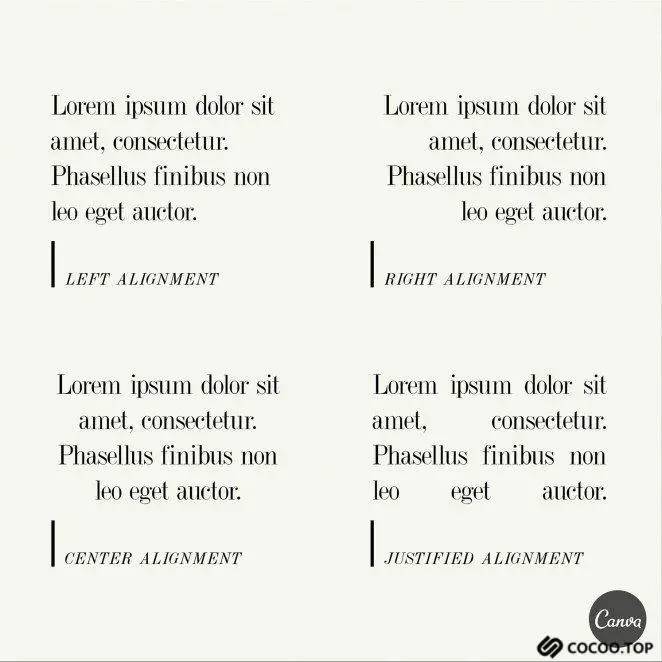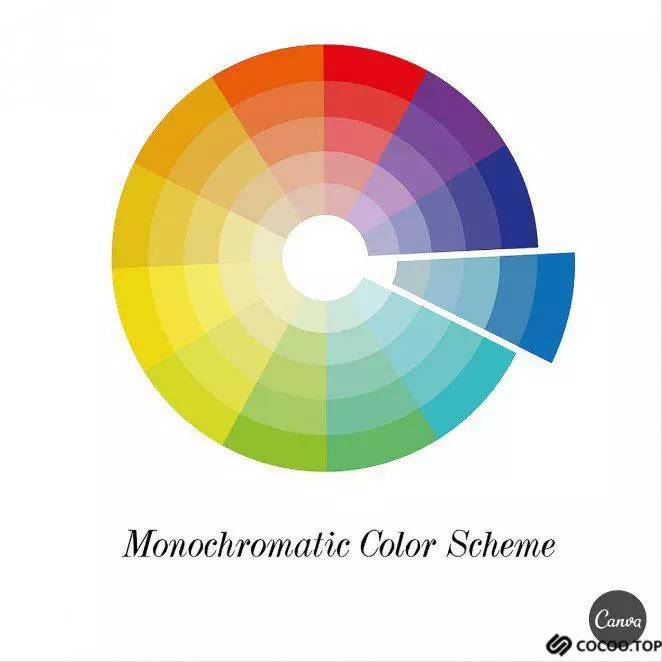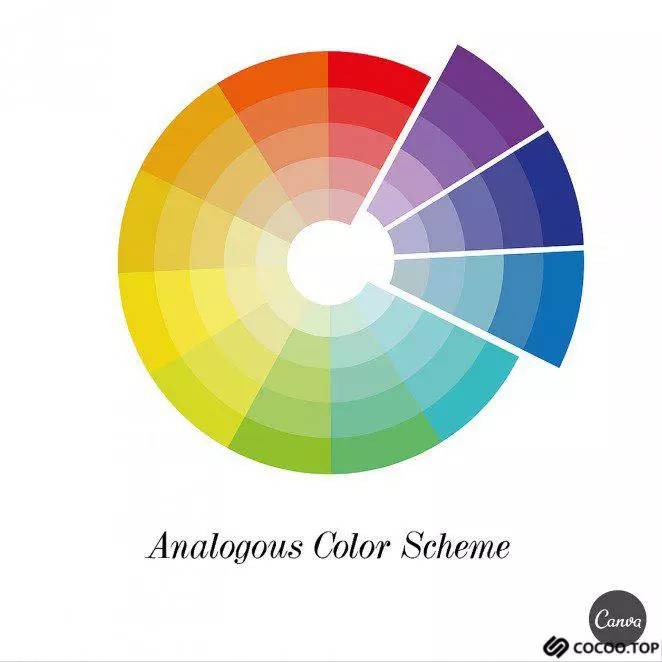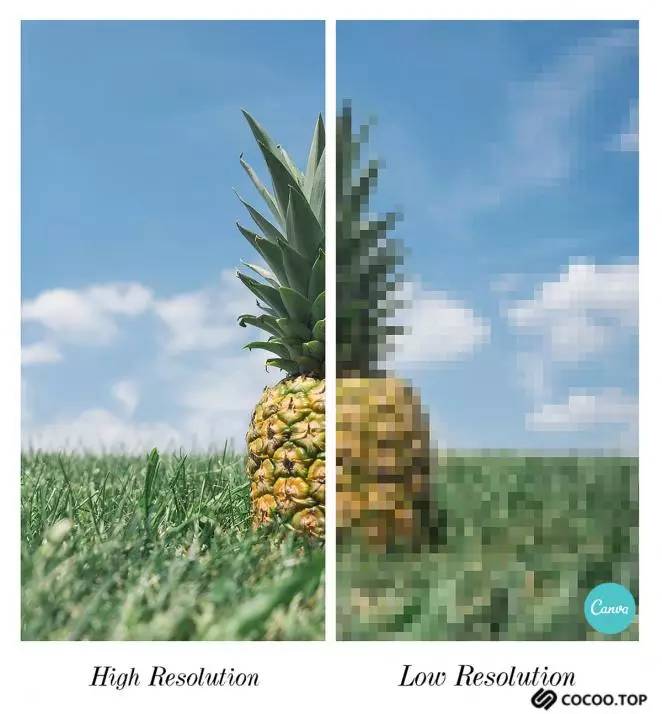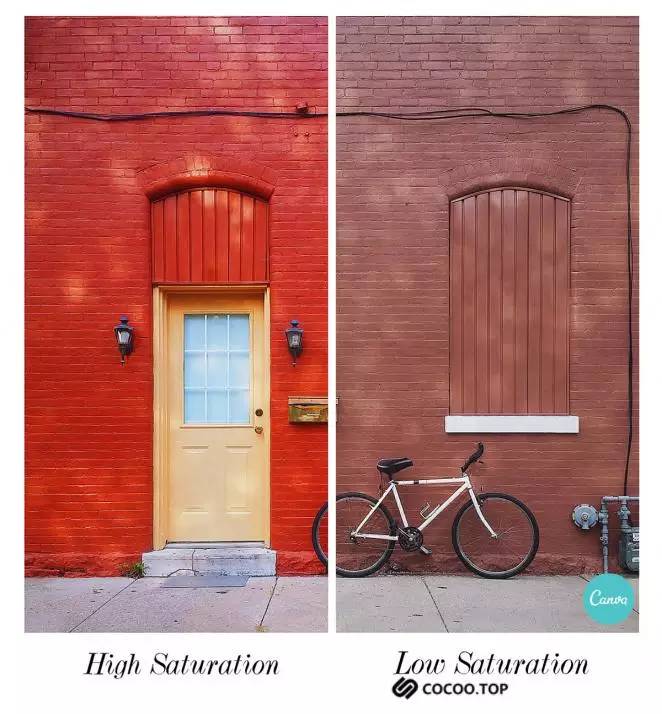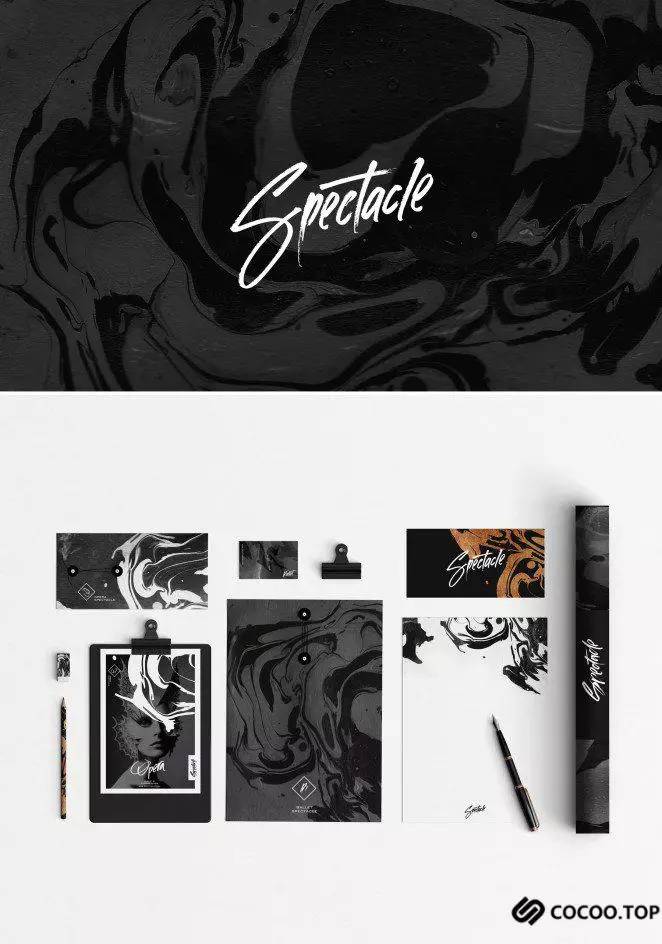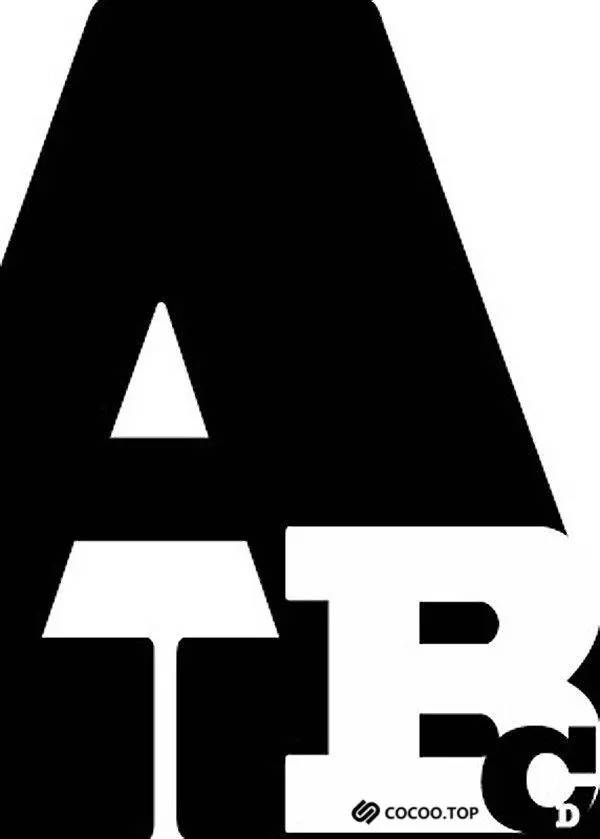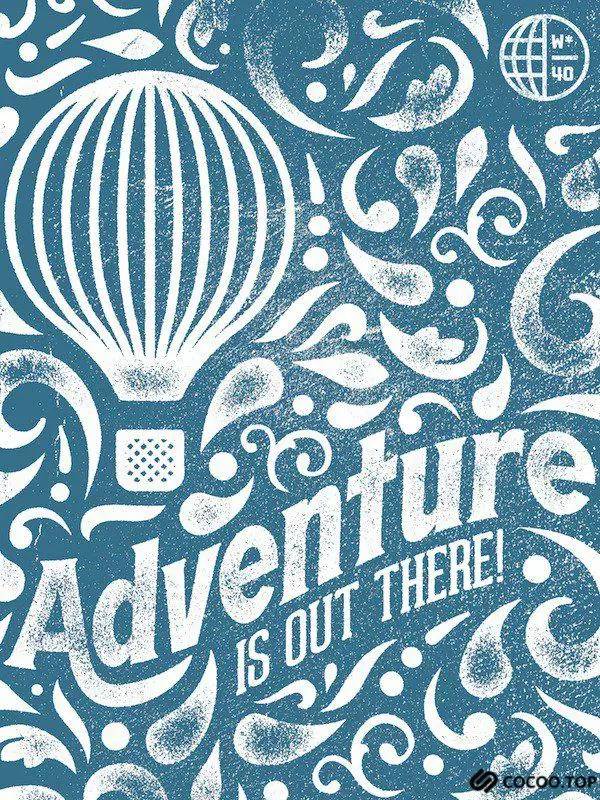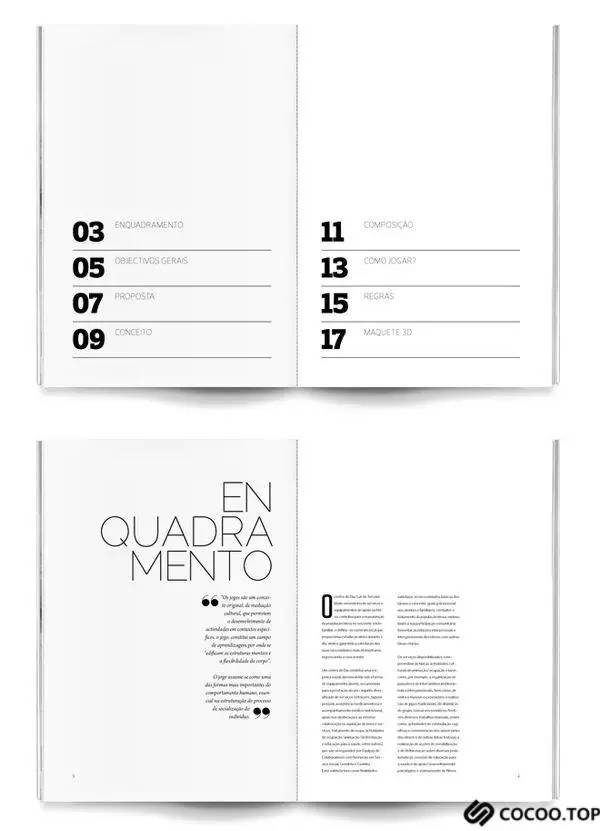
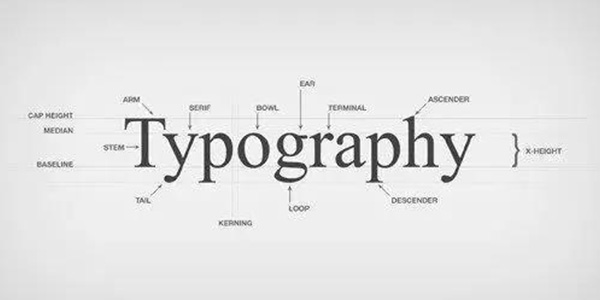
专业设计词汇总结,你知道几个?
{{tag.name}}初学设计的时候,你会觉得仿佛是在修习一门全新的语言。你总会在书本上、老师嘴里碰到从来没听到过的新词汇,间距、版式、冷色调、暖色调、CMYK、RGB,我了个去。感到迷惑的时候,千万不要抓狂,今天这篇文章就是写给大家的设计术语解释,帮你度过最困惑的入门阶段。
01.排版(Typography)
以更加艺术化的手法将文字等内容排布好,让它们得具备更强的可读性,具备更强的视觉吸引力。排版通常和设计息息相关,并且借助多种多样的字体设计来获得更好的视觉效果和视觉传达。
02. 正文(Body Copy)
设计、书写、初版的文章主体通常被我们称为正文(中文其实挺好理解的),网站中的文章的主体、书籍中的主要内容、甚至你此刻正在阅读都算是某个文章的“正文”。
03. 展示字体(Display Type)
那些被设计得引人瞩目的标题和字体。电影海报中的电影名称、杂志的文章标题、报纸的头条,等等都在此范畴。
04. 层次(Hierarchy)
元素和信息按照重要程度进行视觉设计,展现出来的效果就是层次。正如同大标题的字体加粗,确保能吸引更多的注意力。
05. 字母间隙(Kerning)
英文单词中两个字母之间的间隙并非均匀统一的,调整两个字母之间的间隙能够让整个单词看起来更加均匀平衡。
06. 行间距(Leading)
其实的Leading这个词的读音应该为“Ledding”,它通常指的是两行文字之间的空隙间隔。和字间距一样,它是控制段落的疏密视觉效果的重要指标。
07. 字间距(Tracking)
这里所说的字间距是单词中字母间隙的疏密与否,调整字间距会让每个字母之间的距离都随之变化,它通常是着眼于整体的疏密,注意同字母间隙(kerning)在语境上的差异。
08. x高度(X-Height)
它指的是小写字母的平均高度。之所以为称为x高度是应为通常拿字母x作为参考。
09. Ascender
Ascender 指的是小写字母中高于x高度的部分。诸如字母 b、d 和 f。
10. Descender
Descender 通常指的是小写字母从x下方延伸出来的部分,诸如字母 g、j 和 p。
11. “孤儿”和“寡妇”(Orphans and Widows)
他们通常指的是段落在顶部和底部所留出的较短的行。为了视觉上的美观,通常会尽力通过排版将这些部分隐藏起来。
12. 衬线字体(Serif Typeface)
也就是我们所说的衬线体,它们通常在横向或者纵向的端点处有装饰性衬线(中文中的宋体通常算是衬线体),衬线体通常看起来很传统,给人专业和权威的感觉。
13. 非衬线体(Sans Serif Typeface)
没有装饰性衬线的字体(中文中的黑体等通常算在此列),非衬线体通常看起来更加现代、时尚、整洁。
14. 手写字体( Typeface)
模仿手写笔记的字体(中文中这类字体很多,张海山系列的手写体几乎都算),手写字体常常看起来优雅而有性格。
15. 厚衬线体(Slab Serif Typeface)
这类衬线体的衬线通常会更加粗壮,多用于标题,很少出现在正文中。厚衬线体通常会追求更厚重、更稳固、更权威的视觉体验。
16. 可读性(Legibility)
字母在视觉上区分度的指标,可读性涉及到的因素很多,包括字体的大小和类型的选取,通常越简单的字体越适宜于使用小字体的场合。
17. 对齐(Alignment)
各种元素在视觉边缘上保持齐平,按照顺序或者逻辑进行布局。排版印刷上所说的对齐通常有四种,居中对齐、左对齐、右对齐和调整对齐,它们都有对应的使用场合。
18. 引用(Pull Quote)
从正文中摘出一段文字放大,并用作一种分割和强调的视觉元素,呈现你认为重要的文字内容。在杂志的版面设计上非常常见。
19. 调色板(Palette)
你所选取的用于你的设计中的各种色彩,也就是配色方案。
20. 单色(Monochrome)
设计的时候只使用一种色彩,或者使用某一色调的深色和浅色。
21. 类似色(Analogous)
使用色轮中彼此相邻的三种色彩来作为配色方案。
22. 互补色(Complementary)
使用色轮上相对位置的两种色彩来进行搭配
23. 三色(Triadic)
使用色轮上互呈120度角度的三种色彩搭配
24. CMYK
CMYK 四个字母对应的是四种不同的色彩,青色、品红、黄色和定位版套色(黑色),他们是印刷时用的一种套色模式。这种配色方案中,加入的色彩越多,最后生成的色彩越接近于黑色。
25. RGB
RGB 是工业色彩标准,其中三个字母分布标识红色、绿色和蓝色,它们也代表三个通道的色彩,RGB和CMYK不同的地方在于它是一种叠加色,加入的色彩越多,整个色彩越接近于白色。
26. 彩通色(Pantone ,PMS)
PMS,也就是我们常说的彩通配色系统,这套系统是属于印刷体系的标准化系统,每个色彩都有对应的彩通编号和名称,更易于用来识别色彩。
27.暖色调( Warm Colors)
这种色彩通常会让你想起温度,感到温暖。诸如黄色和橙色,它们往往让人感到舒服、友好、开朗。
28.冷色调(Cool Colors)
那些让人感到寒冷的色彩是冷色调,诸如蓝色、紫色、绿色,等等,这些色彩通常可以营造出冷静、平和的氛围。
29. 色彩理论(Color Theory)
那些研究人们对于色彩的感受也反馈的理论,它通常会涉及到不同色彩是如何唤醒潜意识中的某些情绪。蓝色会让人感到信任和可靠,这也是为什么很多企业会选择蓝色作为主要的色彩。
30. 渐变(Gradient)
颜色无缝地逐步变化,从一种色调过度到另外一种色调,两种色调通常是呈现出线性梯度的,从左到右,或者重中间到边缘。
31. 不透明度(Opacity)
通常用作元素透明度的指标,不透明度越低,透明度越高。
32. 分辨率(Resolution)
图片所能呈现的细节的精细度。一般而言,较高分辨率的图片,所呈现出来的细节越多,效果越好。
33. 对比度(Contrast)
两个并列元素之间的差异程度,黑和白,深和浅,粗与细、厚和薄,都是对比。
34. 饱和度(Saturation)
这是颜色强度和鲜明度的指标。低饱和度的图片会显得苍白,或者是褪色的效果,而高饱和度的图片会显得鲜艳而充满活力。
35. 高清图片(Stock Photo)
这里所说的Stock Photo通常指的是出自专业摄影师之手且有授权的优质高清图片。当然,我们非常喜欢授权可商用的免费Stock Photo……
36. 三分法(Rule Of Thirds)
三分法理论,借助两横两竖将图片分割成为9个部分,交叉处为图片的重要部位,或者设计重心。
37. 品牌(Brand)
品牌是涵盖公司价值的理念、想法、情感和形象的合集。
38. 品牌识别(Brand Identity)
也就是大家常说的BI,将品牌设计视觉化,用一个具现化的形象来代表公司的价值、品牌的精神。它所涵盖的外设包括标识、名片、信纸、制服、包装等等。
39. 字体LOGO(Logotype)
通常这样的字体LOGO是基于公司/品牌的名称或者,经过视觉化的设计之后而构成。诸如谷歌、宜家、迪士尼都是这样的LOGO。
40. 商标(Brandmark)
用视觉化的符号或者形象来作为公司和品牌的标识,最典型的是我们所熟知的苹果公司的LOGO,它使用的是被咬了一口的苹果。
41. 手绘缩略图(Thumbnail Sketch)
并不是所有手绘的标识都是此处说所的手绘缩略图。它特制在概念设计阶段提出的粗略解决方案中的手绘标识,他们通常承载着设计师的概念化设计,这些手绘图随后会输入电脑进行可视化重现。
42. 栅格系统(Grid)
通过横竖线来构建栅格系统,用作设计框架。栅格的出现可以帮助设计人员更好的进行各种元素的排布,确保一致性。
43. 比例缩放(Scale)
将对象进行一定比例的缩放,确保整体外观比例的一致。在较大比例下进行设计可以创造出精致出彩的细节。
44. 纹理(Texture)
模拟真实物体表面材质和感觉的设计。纹理可以赋予设计对象以质感,反映实际的视觉外观。
45. 留白(White Space)
我们也会将其称之为负空间,它通常指的是未填充内容的设计区域。留白在设计中是重要的元素,它赋予设计作品以“呼吸感”,有助于规避复杂的设计,保持干净。
46. 边距(Margins)
围绕页面或者元素的边缘空间,通过增减边距的大小能够创造出疏密不同的视觉效果。
47. 印模割图(Die Cut)
通过在印刷品表面切割出多种不同的形状来阴躁独特的视觉效果。这个通常是在完成印刷之后最后的环节。
48. 烫金(Foil Stamping)
通过热处理将箔纸按压到印刷品表面。
49. Letterpressing
这个是通过金属模具在纸版表面按压出有立体感的形状。
50. 假文(Lorem Ipsum)
也被称为“Dummy Copy”,它通常是不具备真实含义的混乱的填充文本,它会展示出文字在某个排版下的视觉效果。